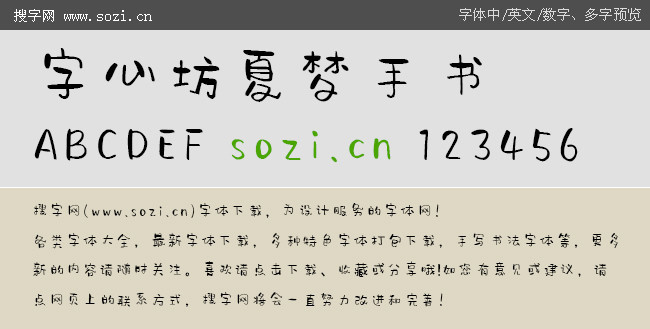
字心坊夏夢手書
搜字網(wǎng)提供一款字心坊夏夢手書中文字體下載, 字心坊夏夢手書是一款主要用于藝術(shù)設(shè)計的字體,該字體風格簡約、清新、時尚、手寫風、有趣,盡顯清新可愛的萌萌噠心情,整體給人非常舒服的感覺,能夠適用于藝術(shù)設(shè)計、包裝印刷、簽名設(shè)計、圖形設(shè)計等應(yīng)用。